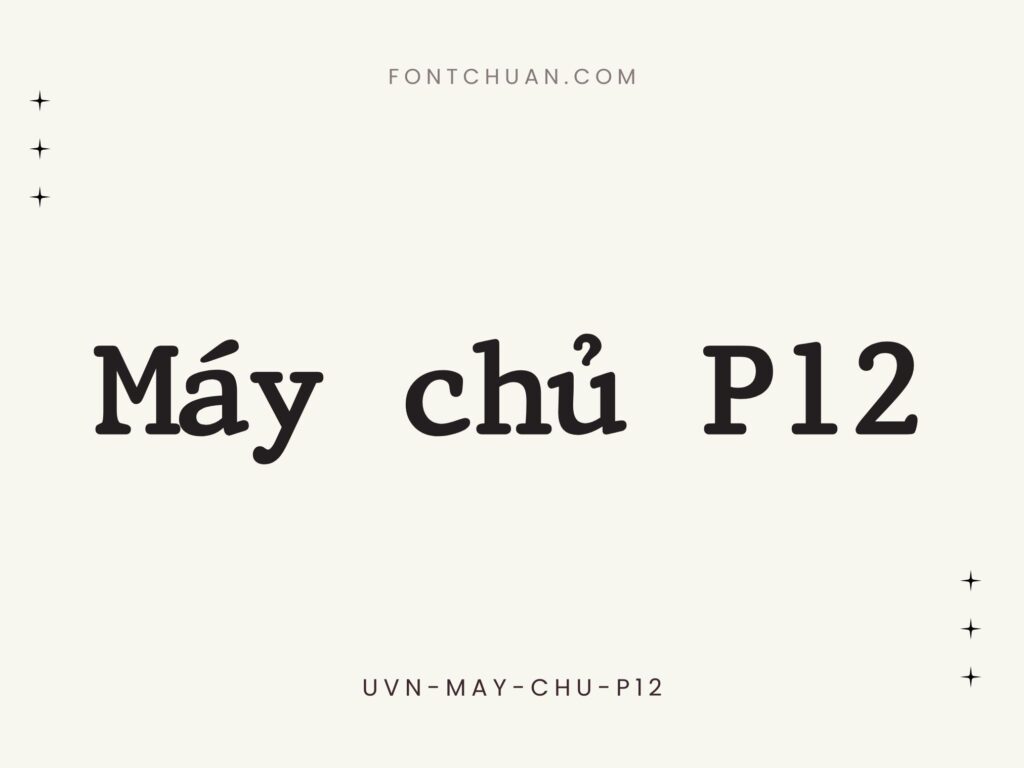
Font UVN May Chu Việt Hóa
UVN Máy Chữ là một Font Monospace lấy cảm hứng từ các máy đánh chữ cổ điển, với các ký tự có độ rộng cố định và đường nét rõ ràng, mang đến cảm giác hoài cổ và chuyên nghiệp. Font này chỉ được sưu tầm và đăng bởi thành viên của Font Chuẩn.
UVN Máy Chữ có cấu trúc chữ với các nét đồng nhất và đều đặn, tạo nên sự dễ đọc và gọn gàng. Font này phù hợp cho các ứng dụng như thiết kế văn bản, giao diện số, tài liệu kỹ thuật và các ấn phẩm in ấn yêu cầu sự chính xác và rõ ràng. Các ngành nghề như công nghệ, giáo dục, quảng cáo và bất động sản có thể tận dụng UVN Máy Chữ để tạo điểm nhấn chuyên nghiệp trong thiết kế.